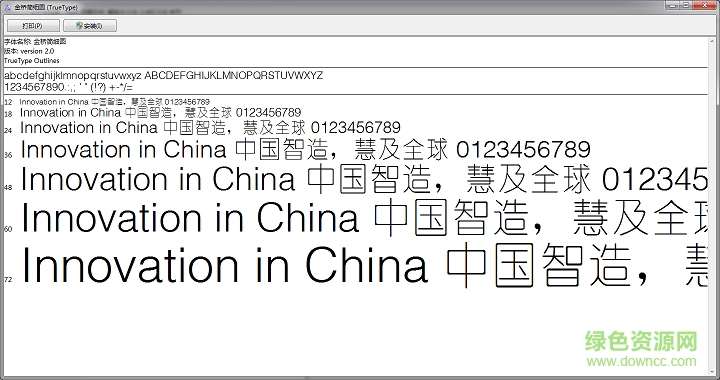
jqxiyuanjt字體是一款細(xì)細(xì)的圓體字體,線條柔和,樸素?zé)o華,大方耐看,可以用作包裝設(shè)計(jì)、女用化妝品、平面設(shè)計(jì)等方面,所設(shè)計(jì)的詞句也非常的具有特色,讓他人一眼就能關(guān)注到,綠色資源網(wǎng)還有更多金橋字體等你下載哦!